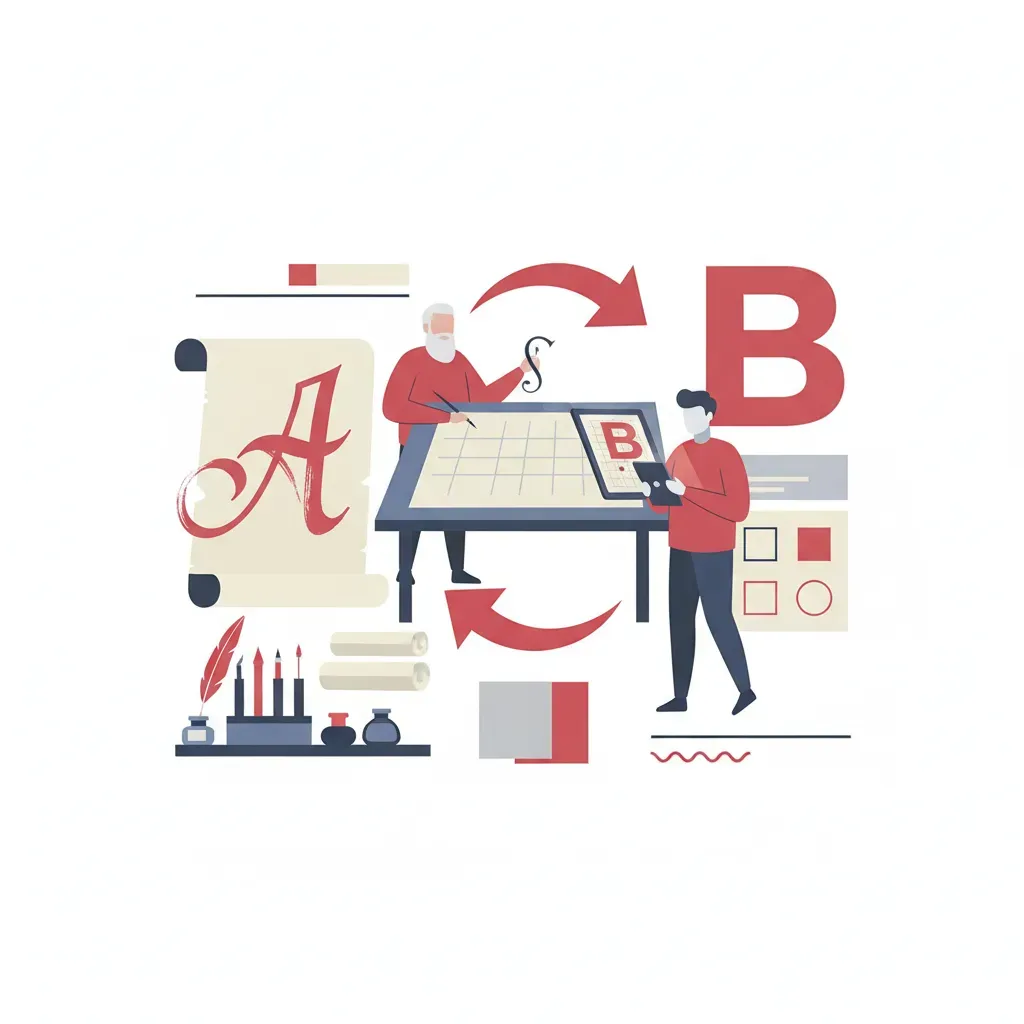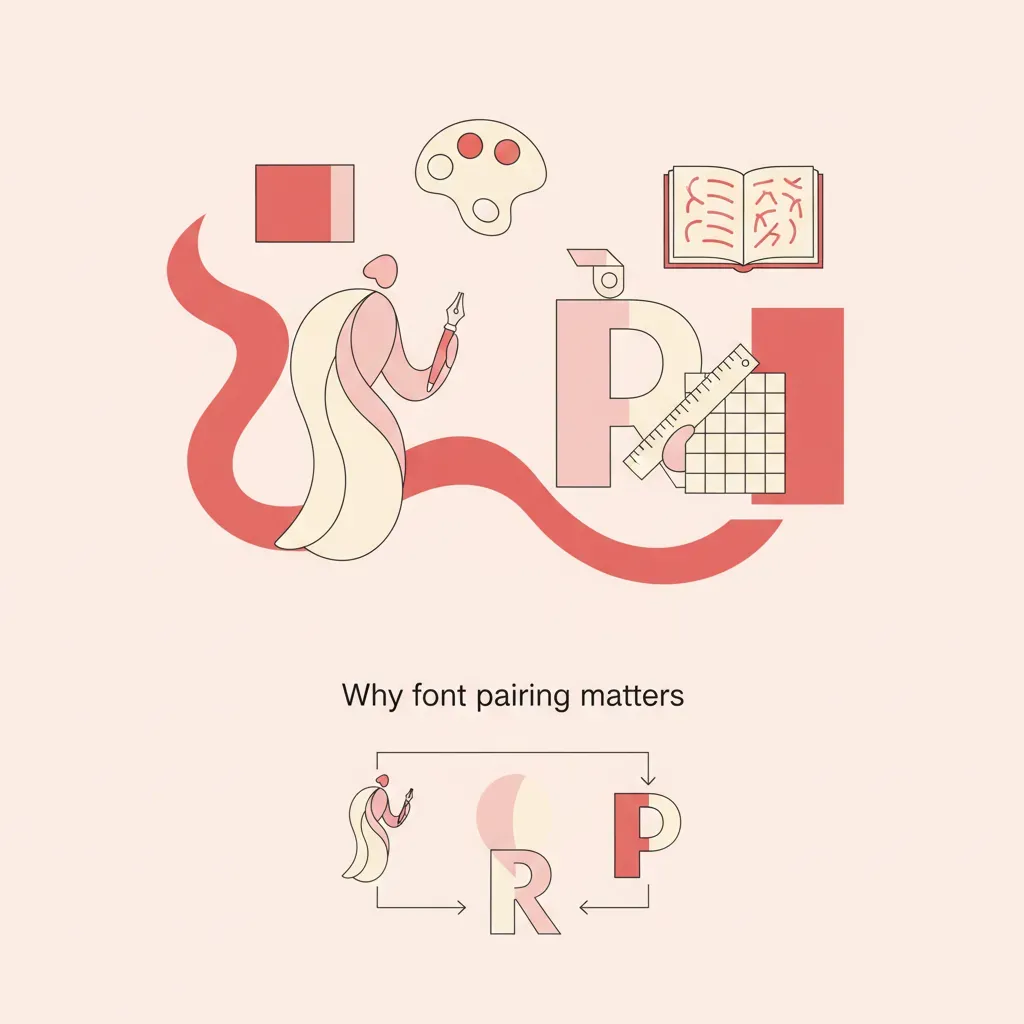
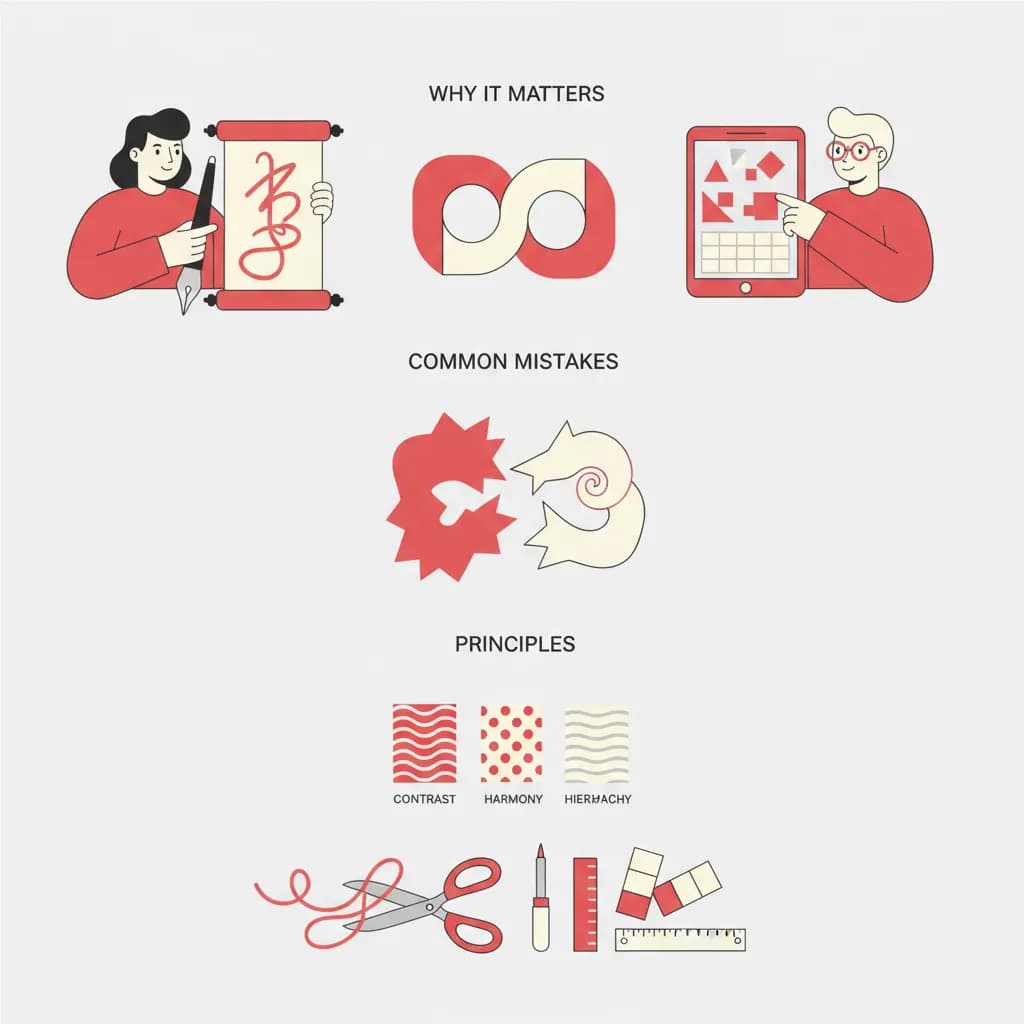
התאמת פונטים היא אחת ההחלטות הטיפוגרפיות המשמעותיות ביותר בכל פרויקט עיצובי. הבחירה הנכונה משפיעה על הקריאות, על האווירה, ועל האופן שבו הקהל תופס את המסר. מעצבים רבים מתמקדים בצבעים ובפריסה, אך מזניחים את הדינמיקה בין הגופנים השונים – וזה בדיוק המקום שבו עיצובים טובים הופכים לעיצובים בלתי נשכחים. מדריך זה מציג את עקרונות התאמת פונטים, השיטות המעשיות, והטעויות שכדאי להימנע מהן.
⚡ נקודות מפתח:
התאמת פונטים היא לא רק עניין אסתטי – היא תקשורת. כאשר שני גופנים עובדים יחד בהרמוניה, הם מנחים את עין הקורא בהיררכיה ויזואלית ברורה: מה חשוב, מה משני, ומה הטון הכללי של הפיסה. לעומת זאת, שילוב גרוע של גופנים יוצר מתח ויזואלי שמבלבל את הקורא ומחליש את המסר – גם אם שאר אלמנטי העיצוב מושלמים.
בעיצוב עברי, האתגר כפול: לא רק לבחור גופנים שנראים טוב בנפרד, אלא לוודא שהם עובדים יחד בשפה שיש לה כיוון כתיבה הפוך, גובה אותיות שונה, ומאפיינים טיפוגרפיים ייחודיים. כפי שמוסבר במאמר האותיות בעברית, מבנה הגופן העברי שונה מהותית מהלועזי, ועובדה זו חייבת להכתיב את תהליך ההתאמה.
מחקרי טיפוגרפיה מראים שהיררכיה טיפוגרפית ברורה משפרת את חוויית הקריאה ומגדילה את זמן השהייה של הקורא עם התוכן. כאשר התאמת פונטים נעשית נכון, הקורא אינו "רואה" את הגופנים – הוא פשוט קורא בנוחות ומבין את המסר.
תהליך התאמת פונטים מקצועי אינו מתחיל בגלריית גופנים – הוא מתחיל בהבנת הפרויקט. לפני שבוחרים גופן אחד, צריך להגדיר: מה אופי המותג? מה קהל היעד? איפה יוצג העיצוב? תשובות לשאלות אלו מכתיבות את כיוון ההתאמה.
תהליך התאמת פונטים ב-5 שלבים:
שלב 1: הגדרת אופי הפרויקט
קבעו מילים שמתארות את המותג: "אלגנטי", "משחקי", "מסורתי", "מודרני". כל מילה כזו מצביעה על קטגוריית גופן מתאימה.
שלב 2: בחירת גופן ראשי (Primary Font)
הגופן הראשי הוא הקול הדומיננטי של העיצוב. הוא ישמש לכותרות ולאלמנטים שמושכים תשומת לב. לפרויקטים רומנטיים, למשל, פונט רומנטיקה הוא גופן מקושט ויפה שמתאים לכותרות ולהזמנות.
שלב 3: בחירת גופן משני (Secondary Font)
הגופן המשני תומך בגופן הראשי ומשמש לטקסט הגוף. הוא חייב להיות קריא יותר ופחות דומיננטי. ריווח בין שורות של 1.5 – 1.7 לטקסט רץ הוא ערך סטנדרטי מומלץ.
שלב 4: בדיקת "גובה x" ומשקל אופטי
כאשר מציבים שני גופנים זה ליד זה, גובה האות הקטנה (x-height) חייב להיות תואם. גופנים עם הבדל גדול בגובה x ייצרו תחושת חוסר איזון ויזואלי, גם אם שניהם מוגדרים לאותו גודל.
שלב 5: בדיקה בהקשר אמיתי
הציבו את השילוב על רקע אמיתי – בגדלים שונים, בצבעים שונים, ובמדיות שונות (מסך, הדפסה, מובייל). התאמת פונטים שנראית מצוינת על מסך גדול עשויה להתמוטט על מסך קטן.
לאחר שנים של עבודה בתחום הטיפוגרפיה העברית, ניתן לזקק כמה עקרונות שעובדים שוב ושוב. התאמת פונטים מוצלחת אינה תוצר של מזל – היא תוצר של עקרונות ברורים שמיושמים בעקביות.
דוגמה 1: עיצוב הזמנת חתונה
הצורך: אווירה רומנטית ואלגנטית. הפתרון: גופן קליגרפי לשמות הזוג וגופן סריפי עדין לפרטים. התוצאה: עיצוב שמשדר חגיגיות מבלי לאבד קריאות. לצורך זה, פונט תפארת הוא גופן סריפי קליגרפי שמתאים בדיוק לשילוב כזה.
דוגמה 2: מיתוג עסקי
הצורך: מקצועיות ואמינות. הפתרון: גופן סנס-סריף נקי לכותרות וגופן סנס-סריף קל יותר לטקסט. התוצאה: מראה מודרני ועקבי שמתפקד טוב בכל מדיה. למשל, פונט קלאסיק הוא גופן דו-לשוני עם מספר משקלים שמתאים בדיוק לצורך זה.
דוגמה 3: עיצוב ספרי ילדים
הצורך: קסם, שמחה וקריאות לילדים. הפתרון: גופן עגול ומשחקי לכותרות עם גופן קריא ופתוח לטקסט. לעיצובים שמחים וקופצניים, פונט בלון הוא גופן נוסטלגי ומשחקי שמתאים לכותרות בפרויקטים כאלה.
לעיון נוסף בעקרונות שילוב גופנים, ראו את המדריך כך תשלבו גופנים עתיקים בעיצוב מודרני שמרחיב על שיטות שילוב מתקדמות.
סוג פרויקט גופן כותרות מומלץ גופן טקסט מומלץ הזמנות חתונה קליגרפי / סריפי מעוטר סריפי עדין מיתוג עסקי סנס-סריף בולד סנס-סריף רגיל ספרי ילדים עגול / משחקי סנס-סריף פתוח אתר תוכן סנס-סריף כבד סנס-סריף קלהכרת הטעויות הנפוצות בתהליך התאמת פונטים יכולה לחסוך זמן וEFFfort. כל אחת מהטעויות הבאות ספציפית לתחום ההתאמה – ולא לעיצוב בכלל.
טעות 1: התאמת פונטים ללא התחשבות בהקשר השימוש
שילוב גופן קליגרפי כבד עם גופן סנס-סריף עדין עשוי לעבוד יפה בפוסטר גדול, אך להתמוטט לחלוטין בממשק אפליקציה. התאמת פונטים חייבת להתחשב תמיד בסביבת הצגה ספציפית – מסך, הדפסה, מובייל, שלט חוצות.
טעות 2: התאמת פונטים עבריים ולועזיים ללא יישור אופטי
בפרויקטים דו-לשוניים, מעצבים רבים מתאמים גופנים לפי שם המשפחה ("שניהם סנס-סריף") מבלי לבדוק את גובה ה-x ואת המשקל האופטי. התוצאה: הטקסט העברי נראה כבד מדי או קל מדי ביחס ללועזי. פתרון: בדקו תמיד את שני הגופנים יחד על אותה שורה לפני קבלת ההחלטה הסופית.
טעות 3: שימוש ביותר מדי משקלים בהתאמת פונטים
יש מעצבים שמשתמשים ב-5 – 6 משקלים שונים של אותו גופן בניסיון ליצור היררכיה. התוצאה היא הפוכה – עיצוב שנראה כאוטי. כלל אצבע: שני משקלים מכל גופן – רגיל ובולד – מספיקים לרוב הפרויקטים.
טעות 4: התאמת פונטים ללא בדיקת ניקוד ותווים מיוחדים
בעברית, גופן שנראה מושלם עלול להיכשל כאשר מוסיפים ניקוד, גרשיים, או תווים מיוחדים. לפני קיבוע ההחלטה, בדקו שהגופן תומך בכל התווים הנדרשים לפרויקט. מידע על גופנים עבריים ב-Google Fonts יכול לסייע בבחירת גופנים שנבדקו לתמיכה מלאה.
הכלל המקצועי הרווח הוא לא יותר משני גופנים עיקריים בפרויקט אחד. גופן ראשי לכותרות וגופן משני לטקסט הגוף – שילוב זה מספיק ליצירת היררכיה ויזואלית ברורה. שימוש בשלושה גופנים ומעלה נדרש רק בפרויקטים מורכבים במיוחד, ואז יש לשמור על עקביות קפדנית בכל שימוש.
לגלריית הגופנים המלאה ←התאמת פונטים מוצלחת היא שילוב של ידע, שיקול דעת, ובדיקה מעשית. הגופנים שבחרתם הם הקול הויזואלי של הפרויקט – הם מגדירים אם הוא ייתפס כאלגנטי, מקצועי, משחקי, או עממי. כל החלטה בתחום התאמת פונטים משפיעה על חוויית הקורא ועל האפקטיביות של המסר.
שלושת עקרונות הליבה של התאמת פונטים: בחרו לא יותר משני גופנים, ודאו שיש ביניהם ניגודיות או הרמוניה מכוונת, ובדקו תמיד בהקשר אמיתי. עם עקרונות אלו, גם מעצב מתחיל יוכל ליצור שילובים טיפוגרפיים שנראים מקצועיים ומשרתים את המסר.